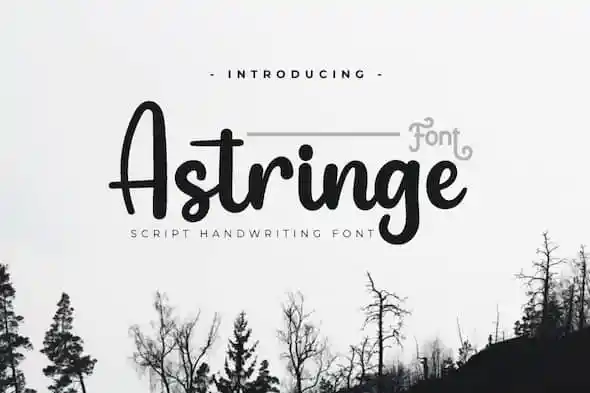
Astringe Script Font – Download Grátis
A Astringe Script Font é uma nova proposta do twinletter, apresentando sua própria personalidade única quando usada nos diferentes meios promocionais e rótulos de produtos. Esta fonte é perfeitamente apropriada para ambientes que valorizam um toque harmonioso e refinado, criando um equilíbrio elegante entre textos legíveis e elementos gráficos interessantes. Seja em uma campanha publicitária sofisticada ou no design de embalagens de produtos, a Astringe Script é perfeita para criar uma conexão emocional com o público. Seu charme natural enriquece qualquer projeto visual, tornando-o ainda mais impactante e memorable. Se você procura uma fonte que combine elegância com personalidade, a Astringe Script Font pode ser sua escolha ideal. Com seus traços suaves e detalhes bem balanceados, essa fonte não apenas se destaca, mas também oferece um tom de mão autêntica capaz de transmitir emoção e conexão em qualquer mídia ou aplicação onde seja usada.